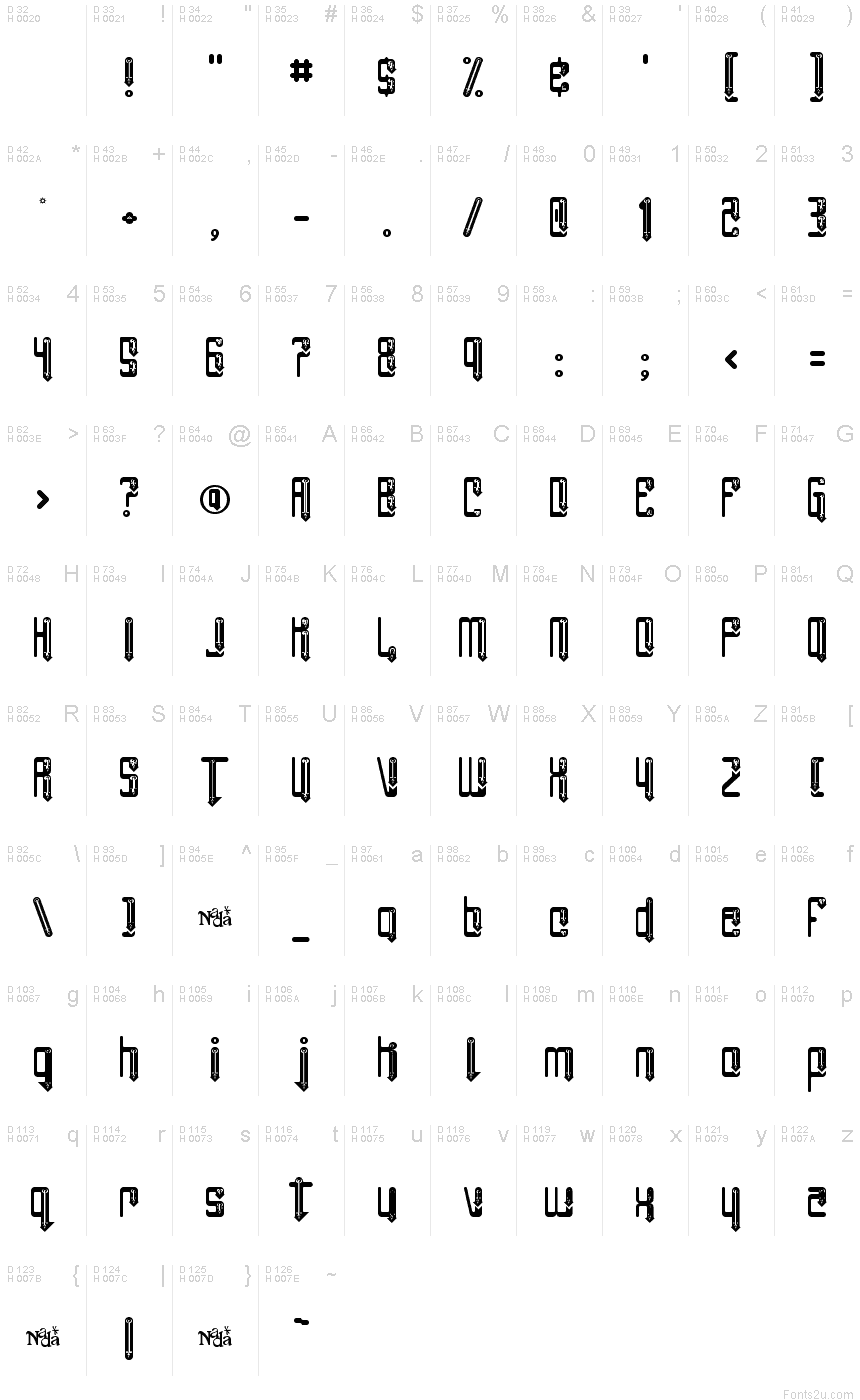
Angie Impressing
Angie Impressing di R.Gast - GreyWolf WebWorks è un carattere display decorativo gratuito che trasforma ogni lettera in un piccolo elemento di segnaletica ornamentale. Le pesanti forme nere terminano con punte simili a frecce, mentre sottili linee bianche attraversano i tratti come circuiti luminosi o filigrane metalliche. Il risultato è un mix di arcano e futuristico: forme solide ricche di dettagli intricati e scintillanti che attirano immediatamente l'attenzione sul tuo titolo.
Con Angie Impressing, le tue parole non si limitano a occupare la pagina, ma pendono come ciondoli o indicano come segnali. Questo font gratuito è perfetto per poster di concerti, copertine di libri fantasy o gotici, titoli di giochi, branding esoterico, loghi di caffè a tema e inviti a eventi audaci. Usalo in dimensioni grandi affinché le linee interne rimangano nitide e abbina Angie Impressing a un carattere sans serif geometrico semplice per il corpo del testo, in modo che non entri in competizione con le sue frecce e linee caratteristiche.